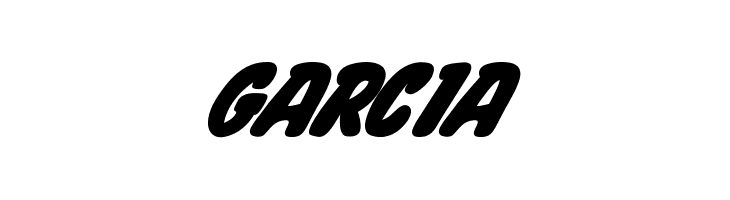
An ornate and decorative font with theatrical flourishes and vintage charm.
A bold, playful typeface with rounded, bubbly characters and a smooth, glossy appearance.
A dynamic, futuristic italic font with angular, geometric characters.
A modern, handwritten font with elegant curves and a dynamic style.
A bold, distressed font with a textured, artistic style.
A bold, futuristic font with sharp angles and an italic slant.
Minimalist, ultra-light geometric line icons.
A bold, 3D font with sharp edges and a modern, impactful style.
A sleek, modern typeface with geometric influences and a minimalist aesthetic.
A bold and italic font with rounded strokes and a modern, dynamic style.
An artistic display font featuring stylized face images within each character.
A bold, geometric font with a modern, condensed style.
A sleek, futuristic, and italicized font with geometric shapes and consistent stroke thickness.
A bold, angular serif font with a modern and edgy style.
A playful font with each letter integrated into a cat silhouette, offering a whimsical and decorative style.
A bold, dramatic serif font with sharp, angular serifs and a modern, edgy style.
A modern, oblique font with sharp lines and geometric influences.
A bold, geometric font with futuristic cut-out shapes.
A playful, bold, and hand-drawn font with a whimsical and friendly appearance.
A bold, energetic script font with a hand-drawn, dynamic style.
The image contains illustrations of beds, not a font.
A lively and elegant script font with flowing, cursive letterforms.
A playful, bold handwritten font with a lively and dynamic style.
A playful, bold outline font with a bubbly, inflated appearance.
A bold, geometric font with an industrial, mechanical style.
A bold, outlined font with a geometric, modern style.
A modern, hollow, inverse font with geometric shapes and sharp angles.
A textured, chalk-like font with a playful, hand-drawn style.
A playful, bold font with rounded edges and a blocky appearance.
A bold, playful script font with a retro vibe and smooth curves.
A bold, decorative font with a vintage, three-dimensional effect.
An elegant, high-contrast script font with a flowing, cursive style.